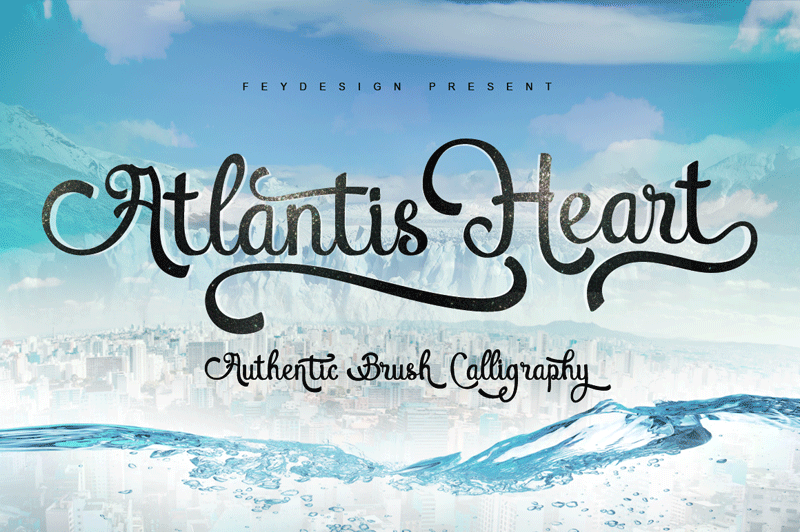
Atlantis Heart Font – Download Grátis
Atlantis Heart Font é uma elegante fonte para escrita chinesa que remete a uma trilha submarina misteriosa. Inspirada na arquitetura magnífica dos corais e nas formas geométricas do coral, essa tipografia tem um estilo autêntico de escrita chinesa que se adapta perfeitamente a diversos usos criativos. Seja para adicionar um toque especial aos designs de elementos da moda, desde estampas até selinhos personalizados; ou para incorporar em logotipos e identidades visuais, essa fonte vai encantar com suas formas delicadas e detalhes sofisticados. Para eventos memoráveis e ramos criativos como o marketing de tênis e materiais promocionais, Atlantis Heart Font é uma escolha brilhante que adiciona um toque único a qualquer projeto. Seja você designer gráfico, ilustrador ou web designer, Atlantis Heart Font certamente será seu aliado para criar designs únicos e memoráveis.
Designer: Fey design